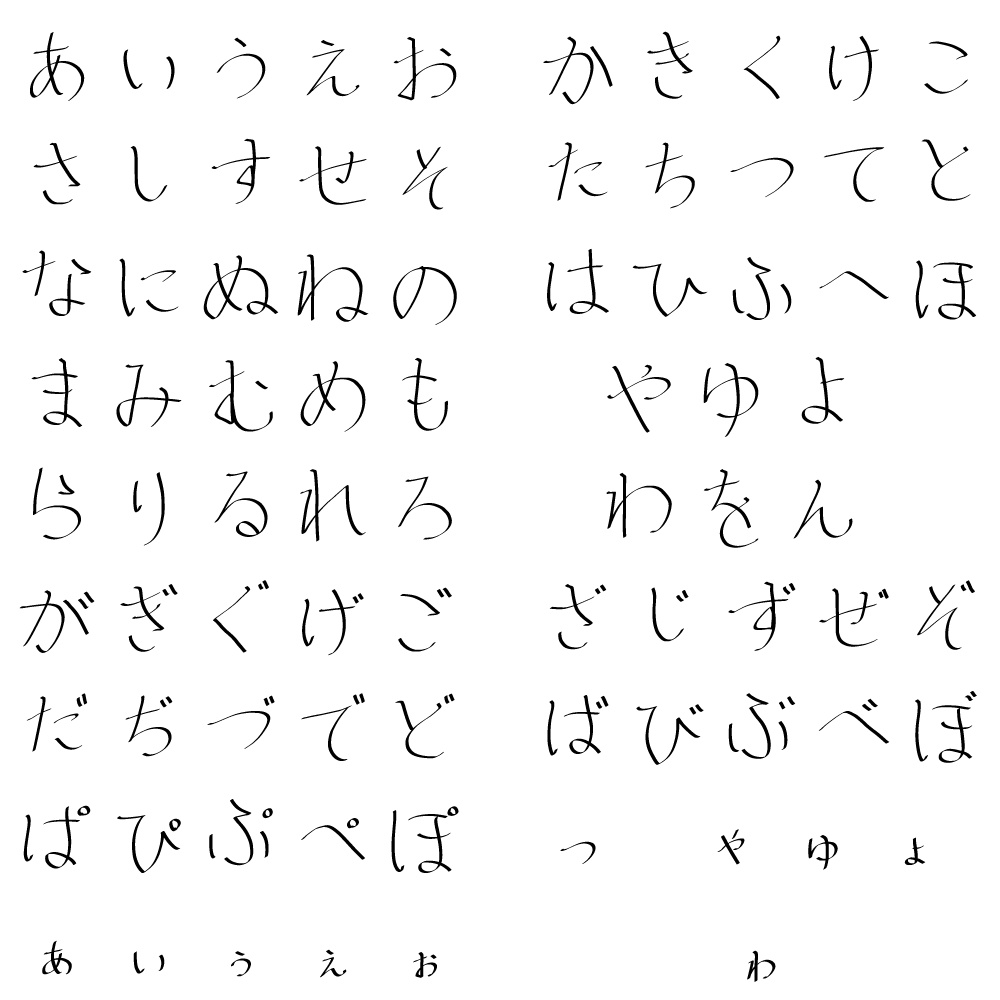
おいらのおにぎりの隠しあ字 只今平仮名のみの対応(フリーフォント)
おいらのおにぎりの隠しあ字 という手書きフォントです。何かの作品とか画像とかにお使いください。 基本無料でフリーですが、お情けでお小遣い程度の額入れてくれてもいいんっすよ((( おいらの気が向けばそのうちカタカナや漢字、記号、数字、アルファベット等...色々対応させていこうとは思ってるので、楽しみにしてくれる方がいれば楽しみにしててください。 初めてこうゆうのつくったので、クオリティとかその他もろもろご容赦ください((( なにか変なことなどあればXのDMまでいただけるとありがたいです。 フォローとかしてもらえると嬉しいかなって感じ! ZIPファイルの中にttfファイルがあります。どの価格も中身は同じです。